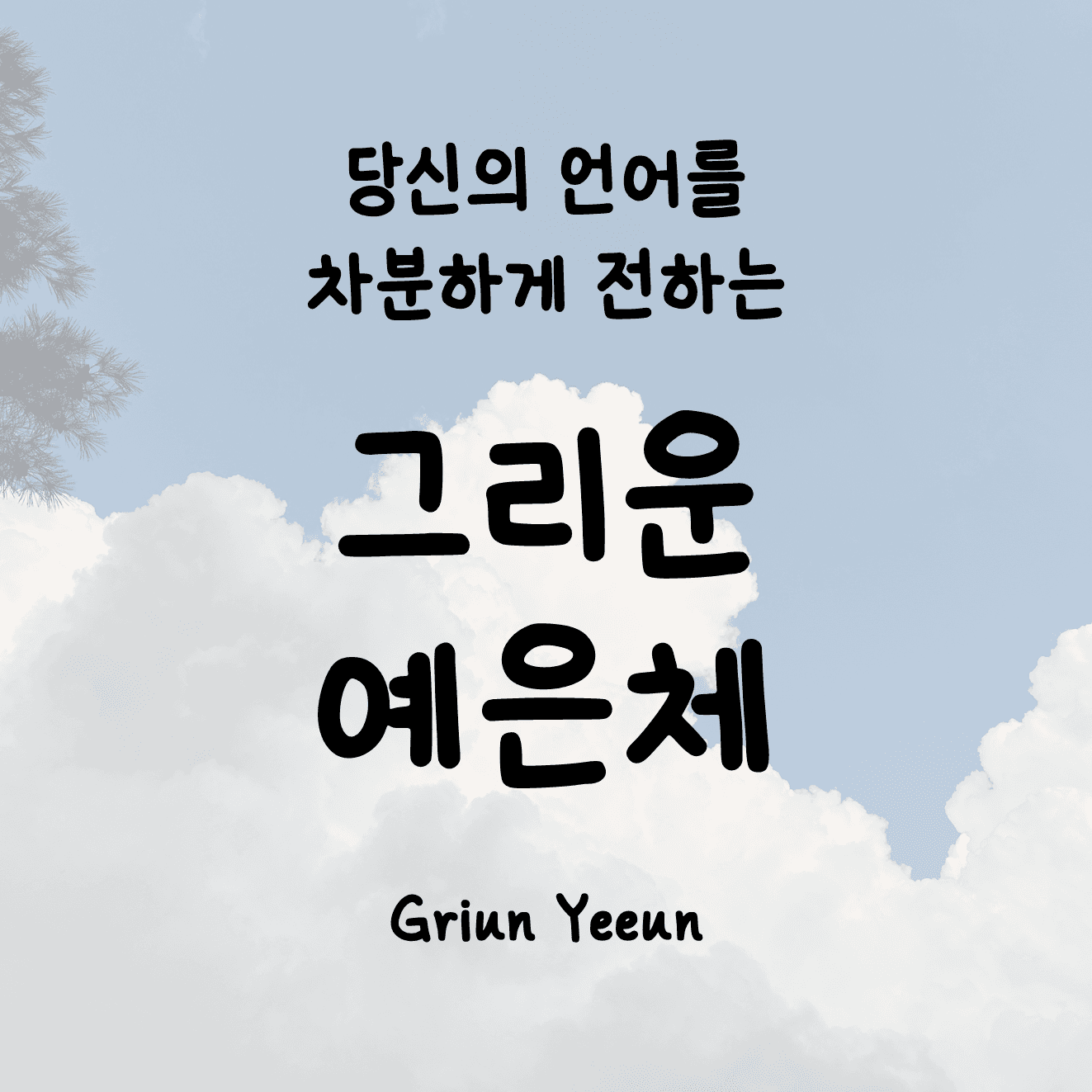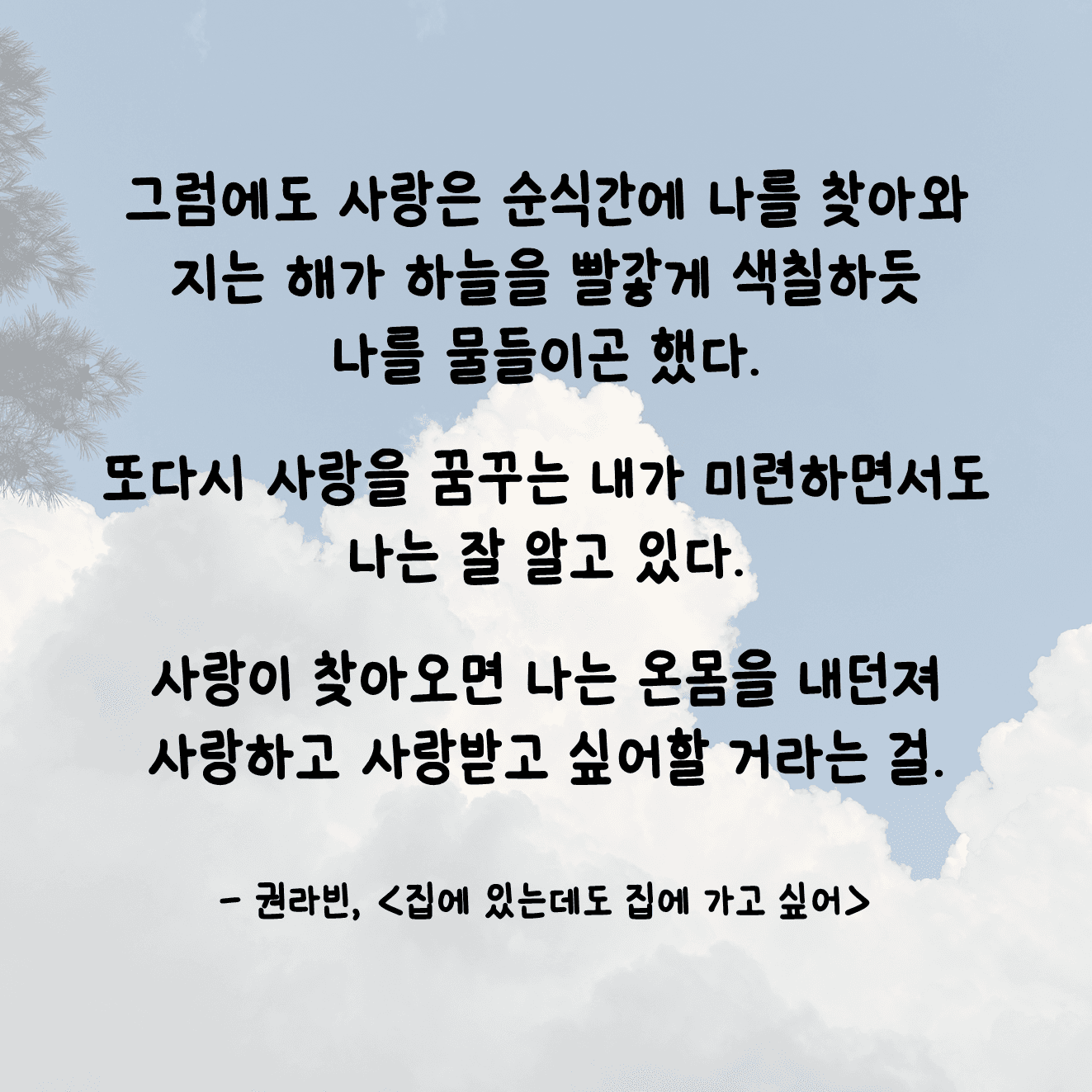
그리운 예은체
Griun Yeeun
그리운 예은체 소개
그리운 예은체(Griun Yeeun)는 차분하면서도 부드러운 저의 성격을 닮은 폰트입니다. 저는 손편지 쓰는 것을 좋아합니다. 온전히 한 사람만을 떠올리며, 그가 좋아할 모습을 기대하며 시간을 보낼 수 있으니까요. 그때의 느린 시간과 조용한 마음을 담아 이 폰트를 만들었습니다. 다이어리, 편지, 노트 필기, 혹은 정갈한 손글씨가 필요한 어느 곳이든 그리운 예은체를 사용해 주세요.